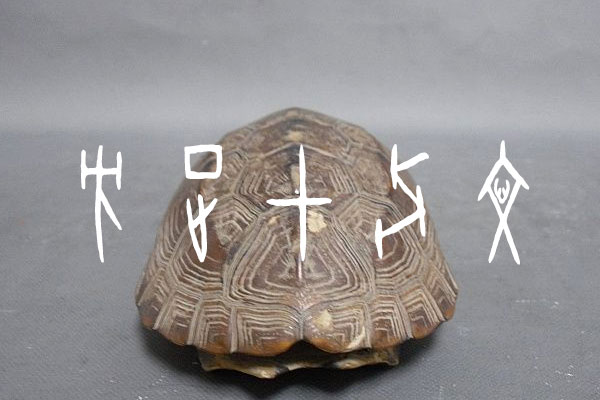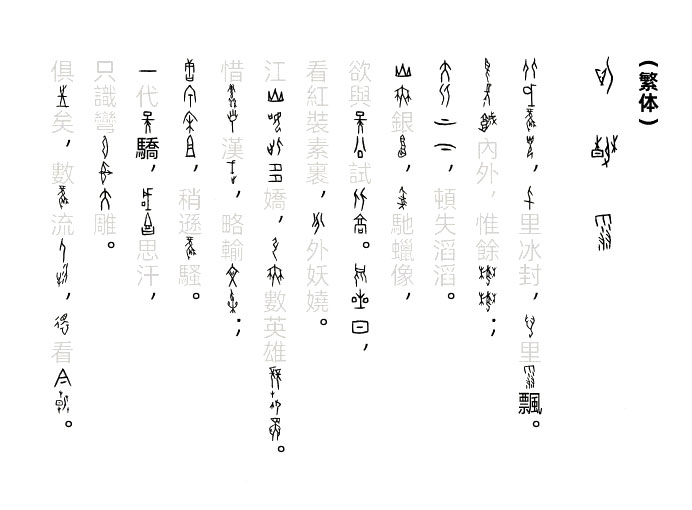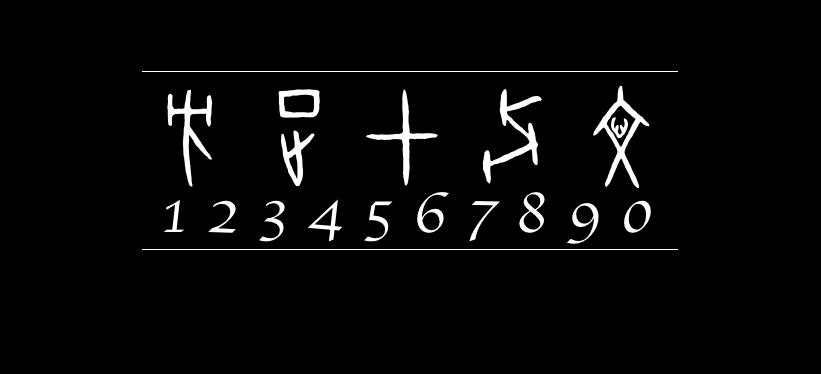
方正甲骨文
甲骨文,指刻写在龟甲、兽骨上的文字。主要发现于河南安阳小屯村一带的殷墟,是商代后期王室和贵族用于占卜和记事的文书,又称契文、甲骨刻辞、卜辞等。所发现的殷墟带字甲骨的数量已有16万片之多,是目前已知中国最早的成体系的文字,主要记载了殷商社会的历史和文化。从甲骨文发现到现在已逾一百二十余年,甲骨文的国际影响力和文化意义日益彰显。
字体特征:
方正甲骨文字库收录字形均在相对公认的已释读的甲骨文范围之内;字形主要以殷墟卜辞原拓和部分周原甲骨文为基础;以典型宾组类为主要字体风格;其字形结体对称而稳定,其线条遒劲坚实、挺拔爽利,曲直粗细均备,笔画多方折。甲骨文字库还原了文字的象形,生动而有趣,又充满了历史的厚重感。需要说明的是,方正甲骨文是基于甲骨文的复刻,很多现在的文字是没有的,不管是简体还是繁体,总共收录了大约一千多字。
设计师:陈宇